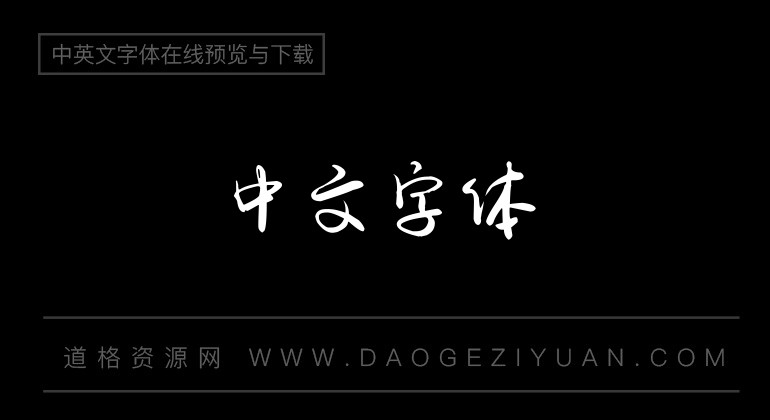
神韵畅游体
神韵畅游体是一款独特的中文字体,由知名字体设计师梁静茹设计,是一款新型的融合字体,它将传统的楷书字体和行书字体融合在一起,形成一种新的字体风格。神韵畅游体在汉字表现上更加细腻,字体笔画更加流畅,更加具有表现力,而且这种字体更加适合用于报刊杂志、网页设计、图片处理、平面设计等等,可以让您的作品更加精致和有趣。
神韵畅游体是一款非常不错的手写艺术字体,具有很好的视觉感,适合于文化类的宣传设计、商业类品牌的广告和产品包装设计以及个性化文字排版等较多场景。